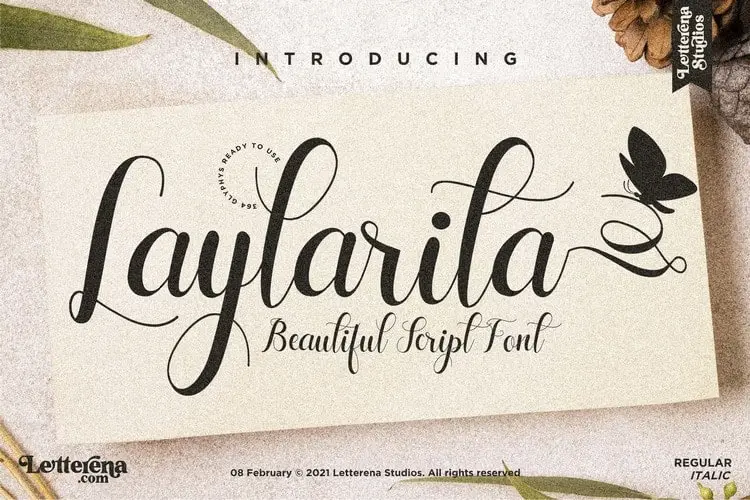
Laylarita Calligraphy Font – Download Grátis
A Laylarita Calligraphy Font é uma nova qualidade do tipo chamada que chega para adicionar um toque romântico a qualquer projeto. Criado pela Letterena Studios, ela se destaca entre as muitas fontes de churrasco disponíveis no mercado. Foi projetada para ser perfeita em uma variedade de trabalhos, desde logotipos e identidades de marca até designs de móveis de casa e embalagens de produtos. Também é ideal para mugs personalizados, tags de frases e cartazes, capas de livro, cartões de nomeador e cartões de convite, etiquetas e até mesmo em fotografias ou em eventos especiais. Esta fonte elegante traz uma verdadeira qualidade ao seu design, transformando qualquer projeto em algo especial e único. E se você está procurando por um churrasco que seja autêntico mas com um toque de sofisticação, Laylarita Calligraphy Font é certamente a opção perfeita para o seu próximo trabalho gráfico.